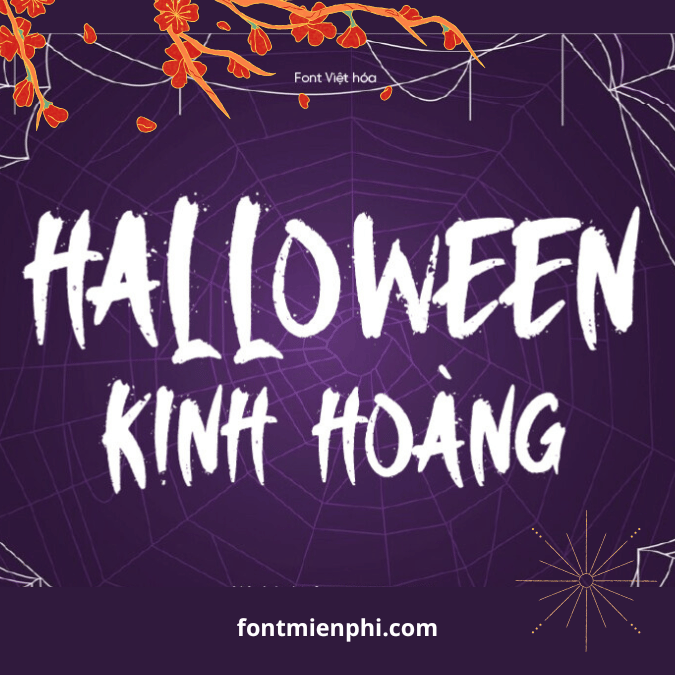
Font Việt hóa 1FTV VIP Zombies Brainless ,font Halloween
Font Việt Hóa 1FTV VIP Zombies Brainless – Phông Chữ Kinh Dị Chất Lượng Cao
1FTV VIP Zombies Brainless là font chữ Việt hóa độc đáo với phong cách zombie rùng rợn, hoàn hảo cho các thiết kế kinh dị, Halloween hoặc dự án mang đậm chất horror. Font được thiết kế tỉ mỉ với nét chữ đứt gãy, vết máu và hiệu ứng “não tan chảy”, tạo cảm giác ma mị, ấn tượng.
Đặc điểm nổi bật:
✔ Hỗ trợ tiếng Việt đầy đủ (Unicode) – phù hợp in ấn, thiết kế, game, phim.
✔ Phong cách zombie, máu me, đáng sợ – lý tưởng cho poster phim kinh dị, áp phích Halloween, truyện tranh horror.
Ứng dụng:
• Thiết kế áo phông, sticker, logo game kinh dị
• Làm video TikTok, YouTube horror
• Trang trí sự kiện Halloween, tiệc ma